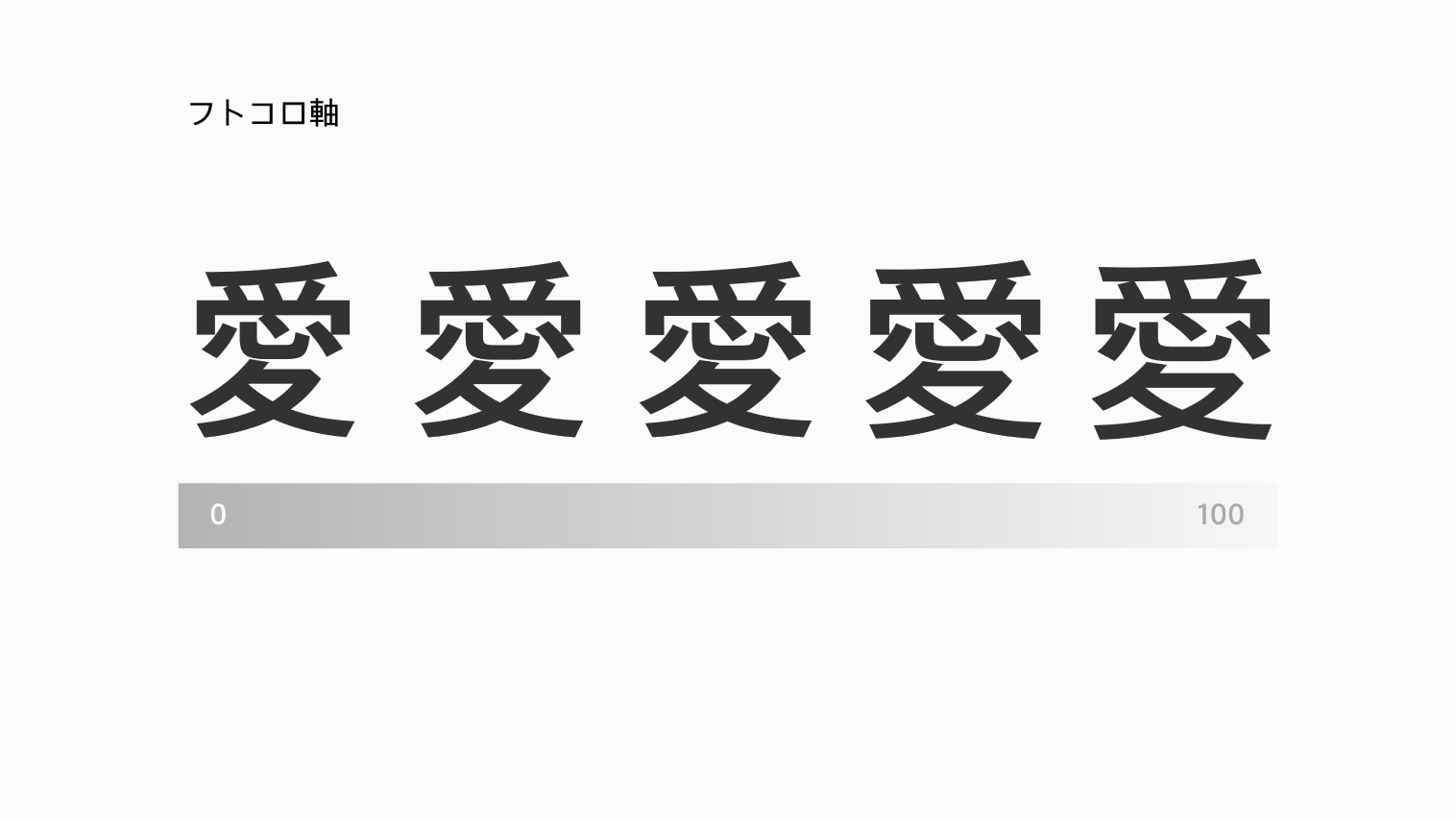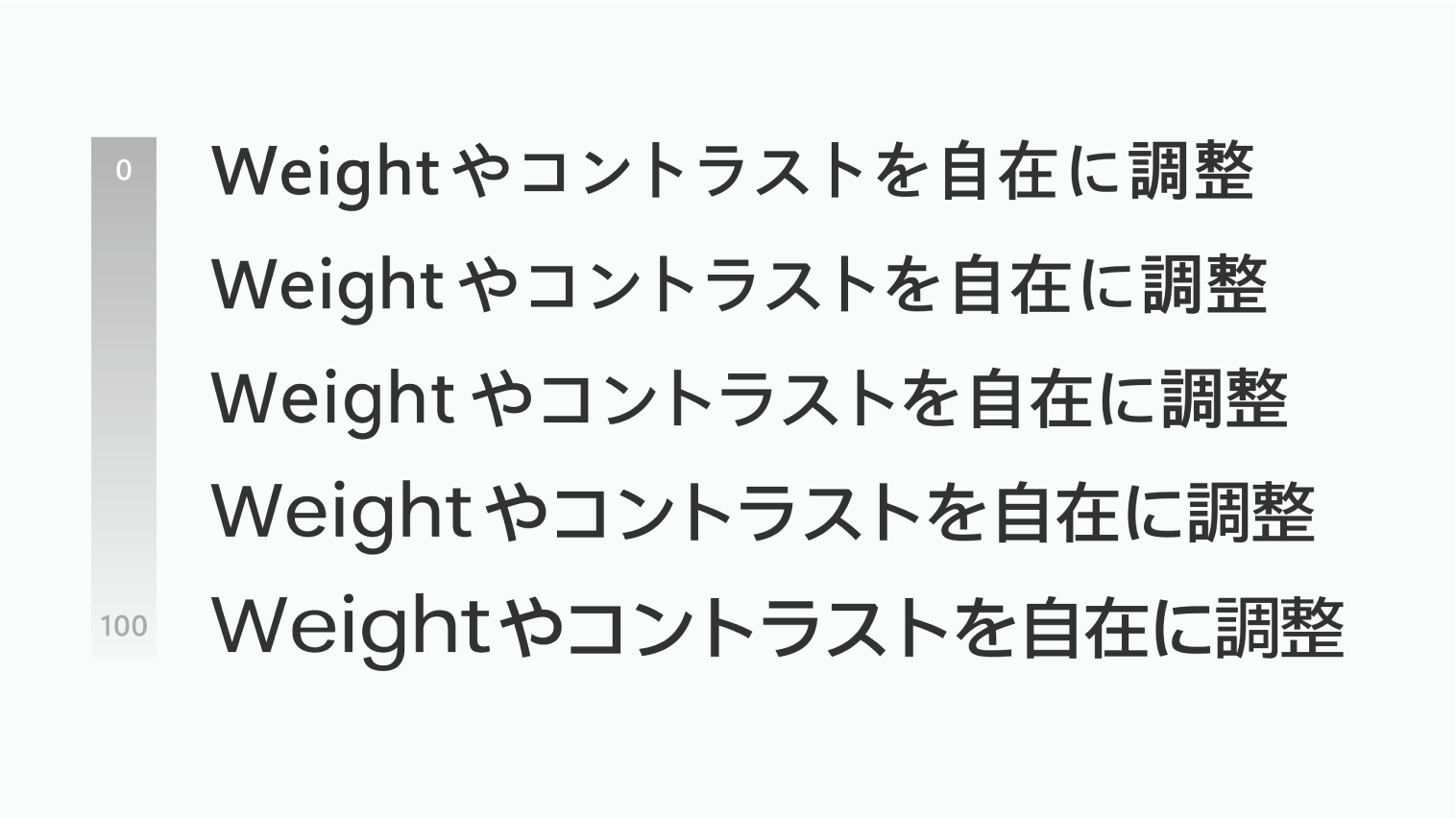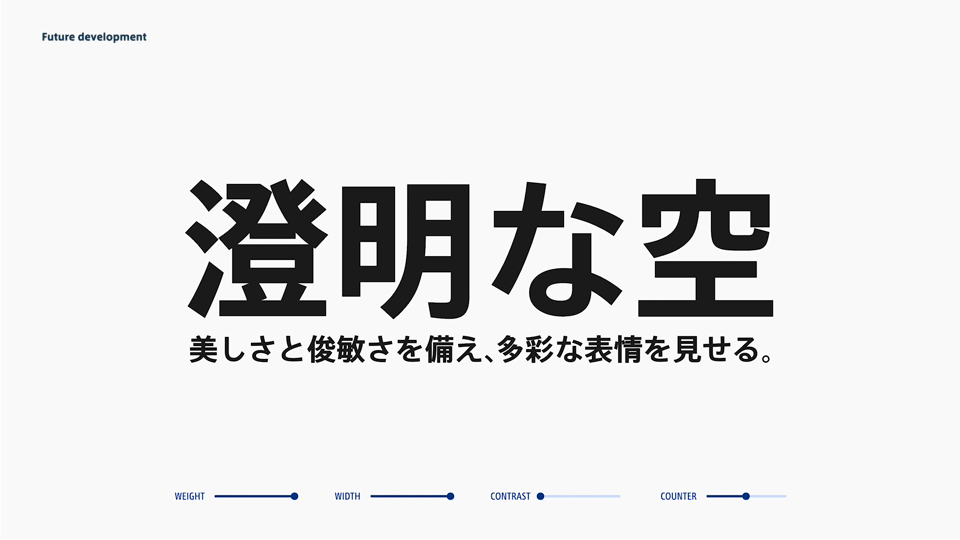
フィットフォントサービスの紹介09「フトコロ軸」
タイププロジェクトではこれまでのフィットフォントサービスによる書体提供の経験をもとに、さらなるサービスの強化のため、技術開発を続けています。
以前の記事で、ウェイト、コントラスト、字幅の3軸を持つ日本で初めての書体ファミリーとして、TPスカイを紹介しました。その次のステップとして4つめの軸を加えたTPスカイを開発し、TPスカイクラシックとして2021年6月にリリースしました。
新しく追加された4つめの軸、それはフトコロ軸です。フトコロとは、文字を構成する筆画同士の間の空間のことを指します。和文書体の骨格を見てみると、クラシック寄りのデザインはフトコロが小さく引き締まった印象なのに対して、モダンなデザインではフトコロが広めの傾向にあります。
フトコロの広さを連続的に変化させるという発想は、少なくとも日本語フォントのなかでは初めてではないかと思います。フトコロの広さはデザインの特徴や雰囲気に大きな影響を与えます。そのため、フトコロ軸を変化させることで得られる表情の変化はとても興味深いものであり、追求していくことでタイププロジェクトのライブラリと技術をより豊かなものにできると私たちは考えています。欧文フォントとのマッチングという意味でも、このような多様な軸を備えたフィットフォントはフィッティングの幅を広げ、バラエティに富んだ書体同士の組み合わせを提供できることでしょう。